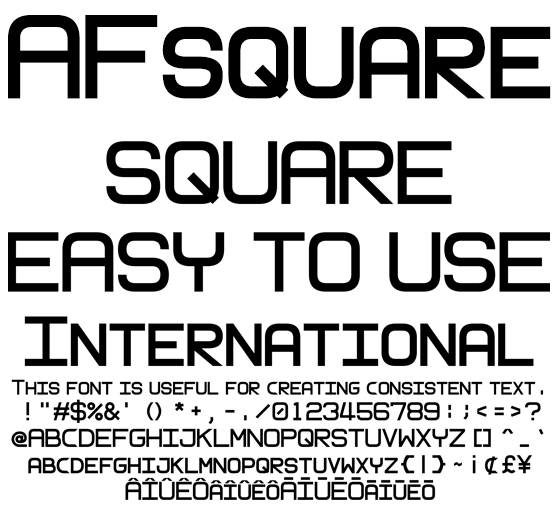
四角ぽいボディな欧文 AFsquare
AFsquare
個々字形の特徴に左右されず縦横が同じサイズで作られた等幅欧文フォントです。統一され縦横にでこぼこがない流れるようなデザインはモダンな表現に最適です。動画のエンドロール、テロップ、液晶表示器、操作パネル、メニューなど幅を統一させたい場所にご利用ください。